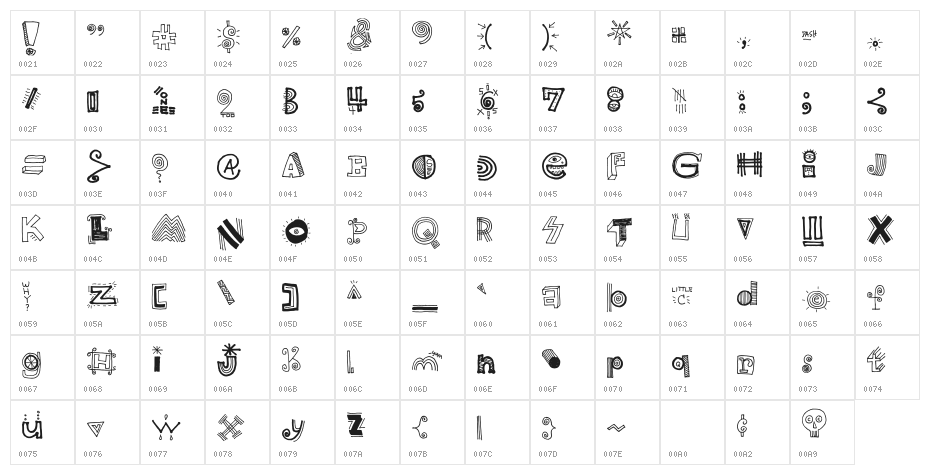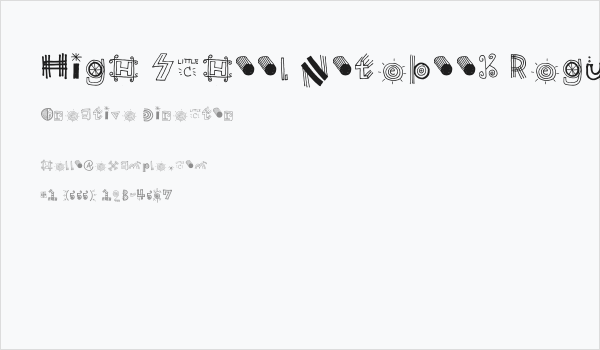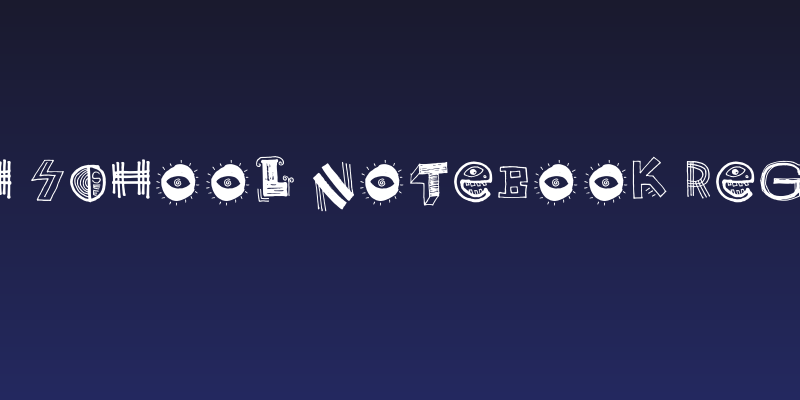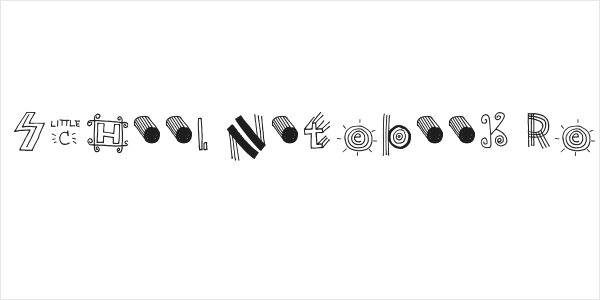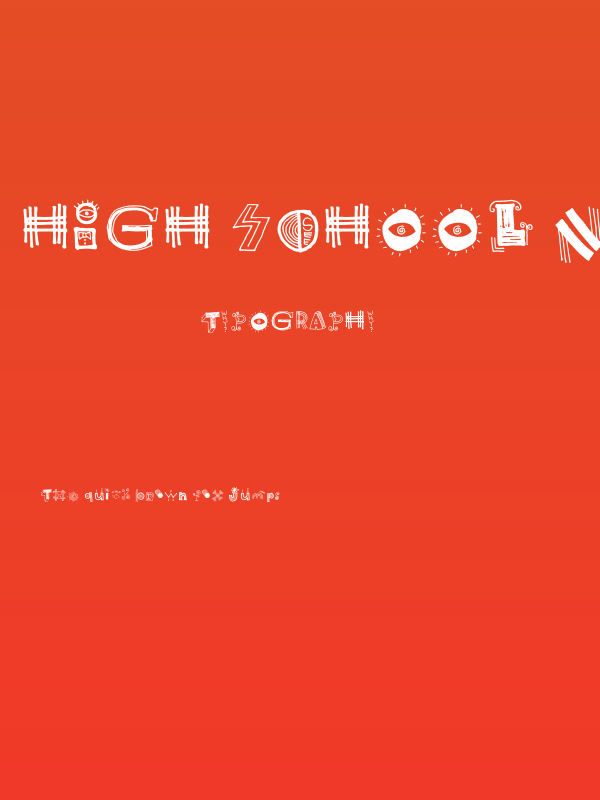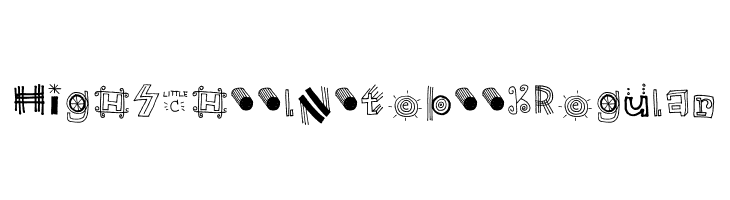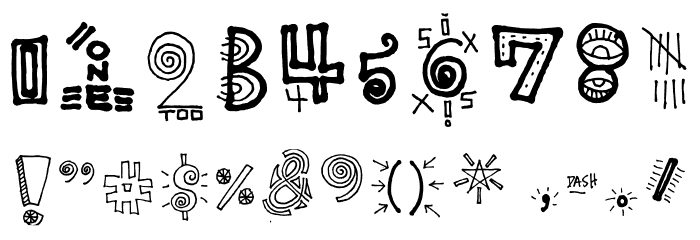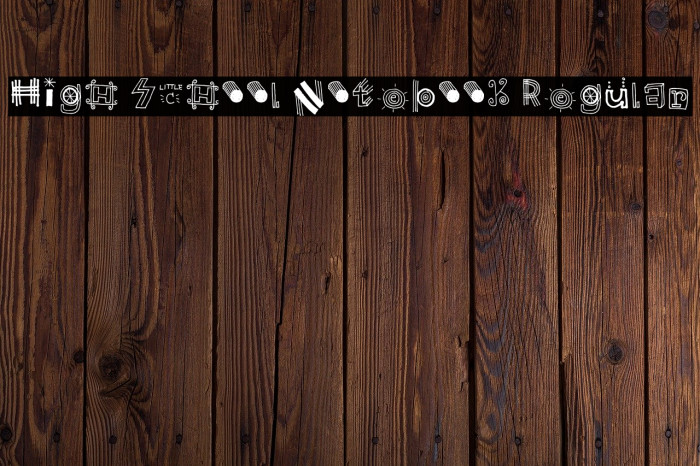
High School Notebook Regular Font
| الاسم | High School Notebook Regular |
| عائلة الخط | High School Notebook |
| النمط العام | Whimsical, Creative, Hand-drawn |
| حالة الاستخدام | Logos, Posters, Creative projects |
| مشاريع مقترحة | Ideal for creative projects such as children's books, playful branding, posters, and invitations. |
| المؤلف | Fonts by Seemly Fonts |